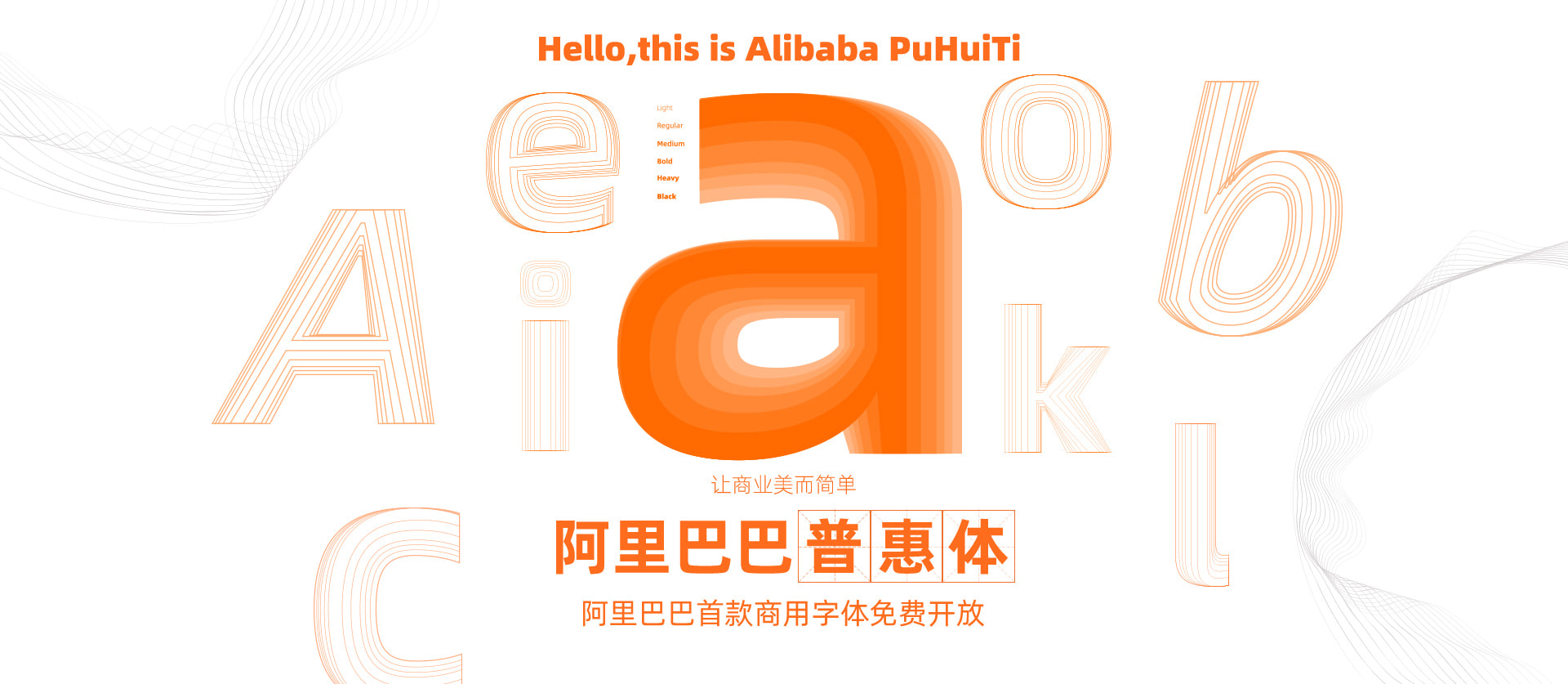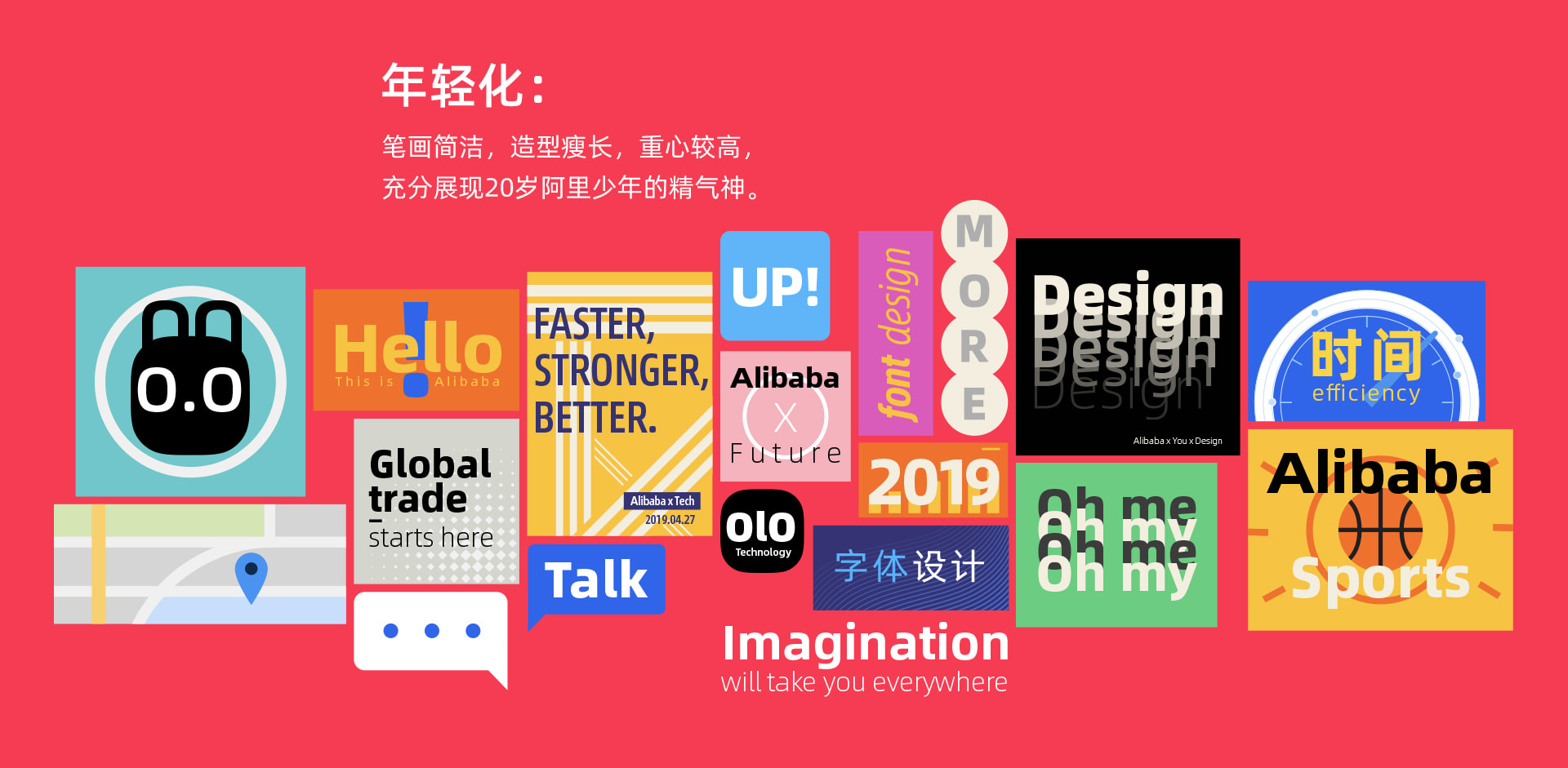
免费商用 | 阿里巴巴普惠体
免费商用的阿里巴巴普惠体共收录 116,895 个全形汉字(含 5 个字重),西文 Alibaba Sans 共 7,205 个拉丁字母(2 种风格、共 11 个字重),覆盖 172 个语种(覆盖大部分欧语国家),并可以满足阿里巴巴集团及其经济体公司在全球化业务下的多个应用场景需求。